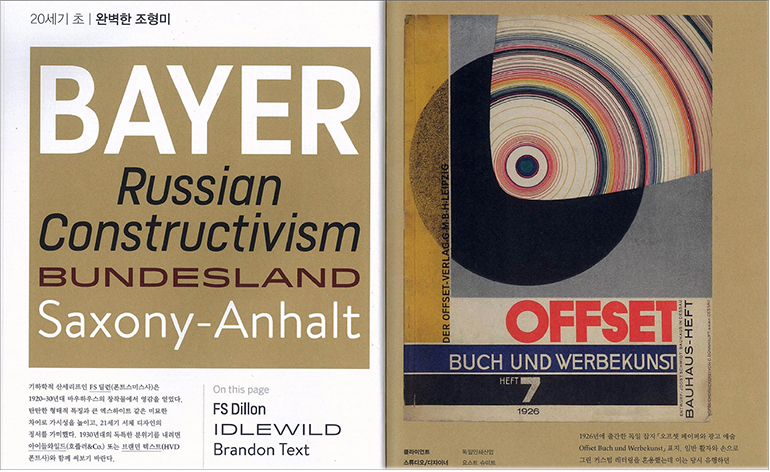
<타이포그래피 × 타입> : 함께 쓸 때 더 좋은 서체 디자인 149
이 책은 더욱 실용적인 관점으로 타이포그래피를 다룬다. 서체를 타입별로 분류하고 무엇과 무엇을 섞어 쓸 때 어떤 느낌인지 직접 보여준다. 이를 통해 ‘서체에도 어울리는 짝이 있다’는 것을 한눈에 파악할 수 있고, 직관적으로 타이포그래피란 무엇인지 깨달을 수 있다.
<타이포그래피 × 타입> : 함께 쓸 때 더 좋은 서체 디자인 149
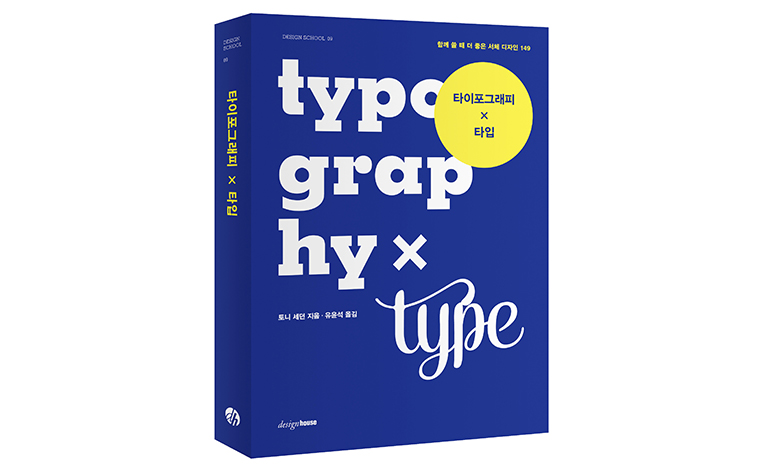
책 소개
서체에도 궁합이 있다! 환상의 하모니를 이루는 서체 조합과 그 이유를 담은 책, <타이포그래피×타입>이 발간됐다. 활판 인쇄술을 뜻하는 타이포그래피(Typography)는 오늘날 문자를 활용한 디자인의 한 분야를 이르는 말로 넓게 쓰이고 있다. 타이포그래피 관련 서적은 활판 인쇄술을 역사적으로 접근해 원리와 용어 위주로 설명하는 개론서가 많은 편이지만, 이 책은 더욱 실용적인 관점으로 타이포그래피를 다룬다.
서체를 타입별로 분류하고 무엇과 무엇을 섞어 쓸 때 어떤 느낌인지 직접 보여준다. 이를 통해 ‘서체에도 어울리는 짝이 있다’는 것을 한눈에 파악할 수 있고, 직관적으로 타이포그래피란 무엇인지 깨달을 수 있다. 타이포그래피를 공부하려는 사람이라면 다양한 스타일을 참고해 영감을 얻을 수 있고, 실무자라면 진행 중인 디자인 프로젝트에 활용해볼 만한 서체를 발견할 수 있을 것이다.
테마에 따라 제안하는 149가지 서체 조합
저자 토니 세던은 20여 년 이상 그래픽 디자이너이자 출판사의 아트디렉터, 타이포그래퍼 등으로 활동해온 베테랑 디자이너이다. 그는 축적된 경험을 살려 함께 썼을 때 더 좋은 149가지 서체 조합을 제안한다. 폰트뷰로사, 폰트스미스사, 개라지폰트사, 포지타입사 등 대표적인 서체 회사들의 200여 가지 폰트 패밀리를 수록하고 있으며, 중세, 20세기 초, 상업, 산업, 테크놀로지 등 32가지 테마에 맞춰 프로젝트별로 함께 쓸 만한 서체를 2~4개씩 묶어 보여준다.
예를 들어, ‘산업’ 테마에서 ‘건축미’를 드러내는 ‘MVB 솔라노 고딕(Solano Gothic)’과 ‘아르마다(Armada)’를 함께 소개하는 식이다. 본문용 혹은 제목용 서체에 어울린다거나, 행정기관의 문서 디자인에 사용하라는 등 시니어 디자이너로서의 노하우가 담긴 팁도 놓치지 않는다. 또한 해당 서체를 이용한 포스터 등 디자인 도판을 덧붙여 풍성하게 구성했다.
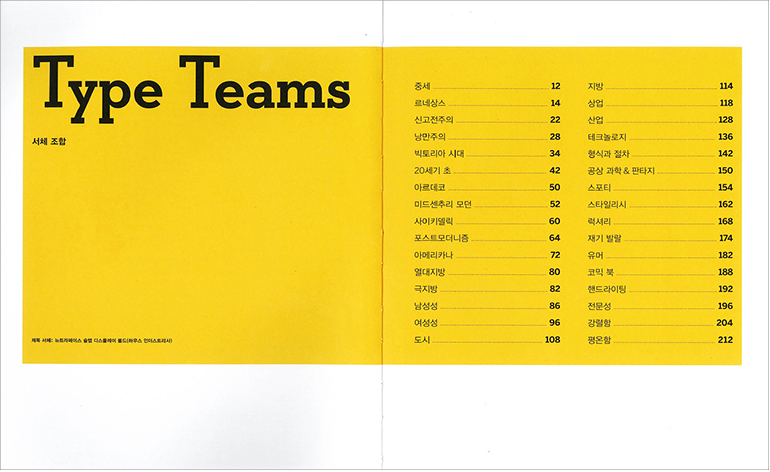
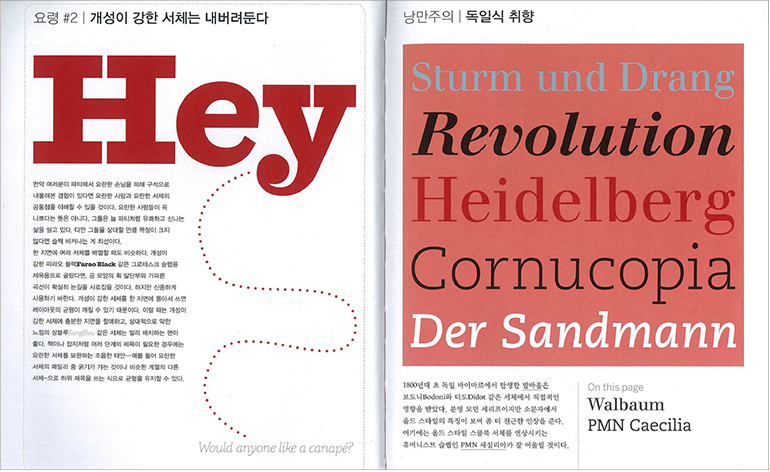
초보에서 프로까지, 디자이너의 서체 안목을 키우는 타이포그래피 실용서
<타이포그래피×타입>은 타이포그래피를 이해하는 데 필요한 기초 지식까지 담고 있다. 대표적인 영문 서체 분류법인 ‘복스 서체 분류법’을 훑고, 글리프, 레그와 테일 등 서체를 이루는 10가지 원리를 설명하며, ‘세리프와 산세리프를 함께 쓴다’ 등 타이포그래피 디자인의 요령까지 담았다. 특히 서체 개발에 얽힌 흥미로운 설명은 서체에 관한 호기심을 부추긴다. 패션지 『하퍼스 바자』에 사용하기 위해 개발됐다는 ‘HTF 디도(HTF Didot)’는 서체에서 스타일리시함이 묻어나고, 독일의 도로 표지판이나 행정 기관의 문서 작성에 사용한 ‘딘 1451(DIN 1451)’에게선 견고함이 느껴진다. 서체의 맥락을 파악한 순간, 타이포그래피 디자인이 한결 쉽게 이해되는 것이다.
<타이포그래피×타입>은 서체에 관해 흥미를 갖고 있는 사람, 서체를 선별할 수 있는 안목을 키우려는 디자이너와 디자이너 지망생을 위한 책이다. 책에서 제안하는 149가지 서체 조합은 지금 당장 적용해볼 수 있는 훌륭한 예시지만 말 그대로 ‘제안’일 뿐이다. 더 좋은 조합, 더 많은 제안은 책을 읽은 당신에게서 탄생한다.
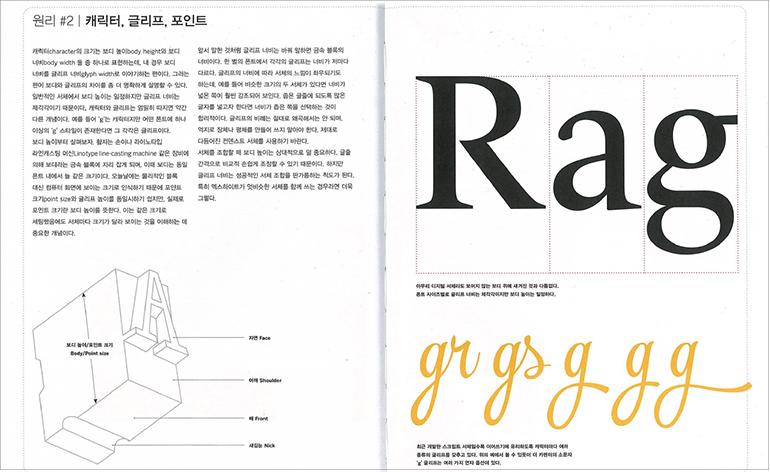
원리 The Principles
스트레스
캐릭터, 글리프, 포인트
대비
애퍼처와 카운터
레그와 테일
어센더와 디센더
단층 또는 복층
세리프 모양과 브래킷
스크립트
글리픽
요령 The Tricks
서체에 대한 편견을 버린다
개성이 강한 서체는 내버려둔다
위계를 세운다
몇 개의 폰트(서체)가 필요할까?
세리프와 산세리프를 함께 쓴다
다양성을 인정한다
패밀리가 풍부한가?
시각적 크기를 맞춘다
일관된 분위기를 유지한다
조화를 생각한다
컬러를 부여한다
리거처를 활용한다
티틀을 조절한다
분수 표기에 유의한다